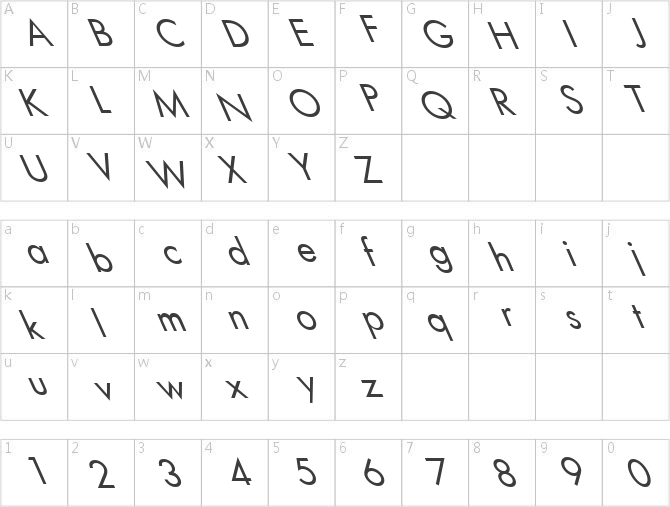
FZ BASIC 18 LEFTY
FZ BASIC 18 LEFTY介紹
FZ BASIC 18 LEFTY字體字庫是一款讓人賞心悅目、百看不厭的英文字體,適合各類廣告和產品包裝設計應用,字體大小0.04MB,格式為ttf字體,上傳用戶是小猴子1003,作者/版權方為未知
FZ BASIC 18 LEFTY效果圖